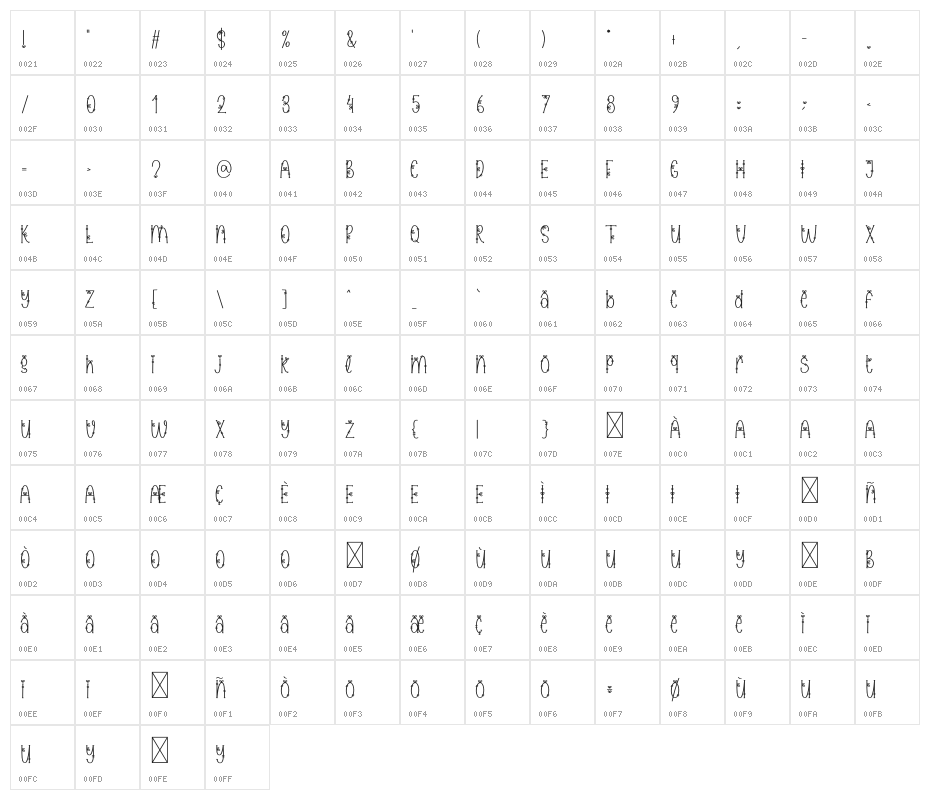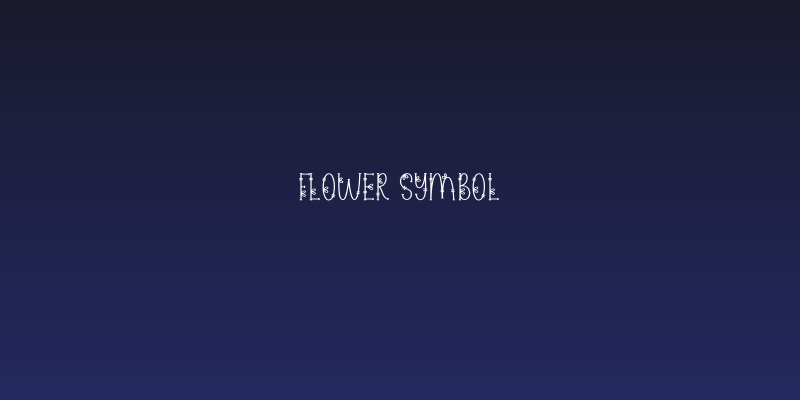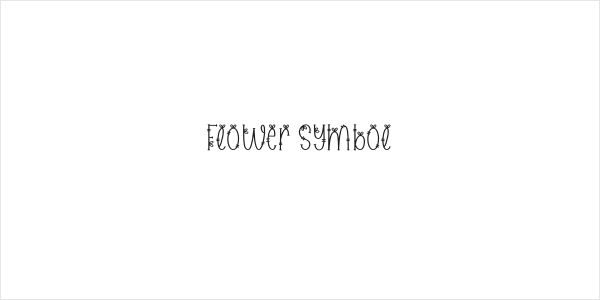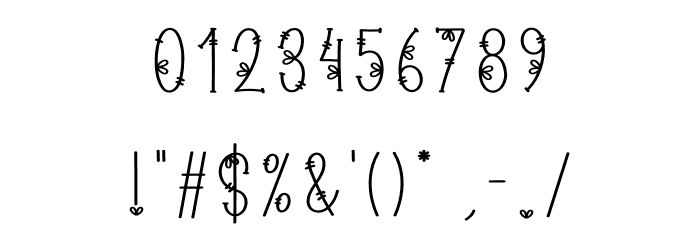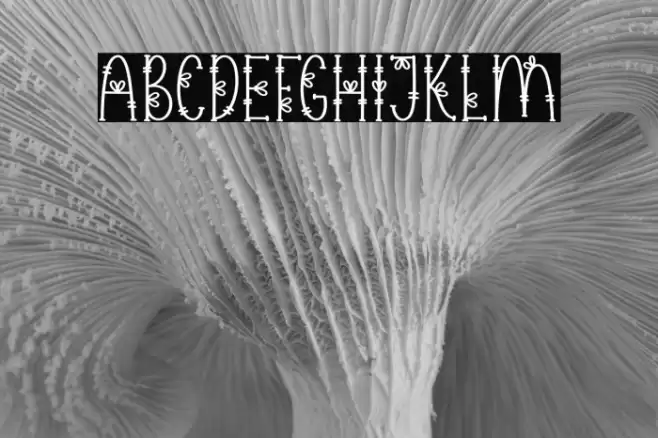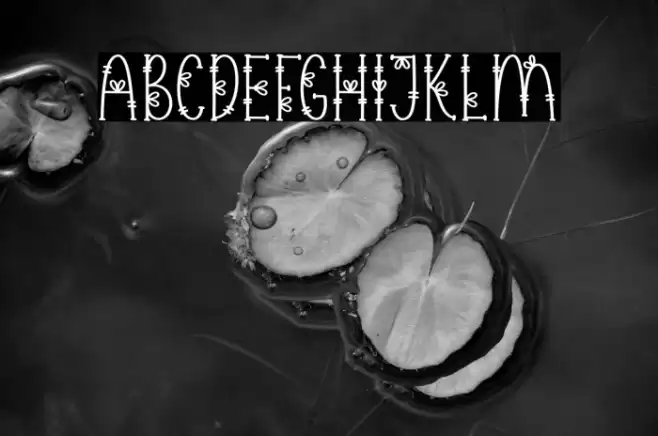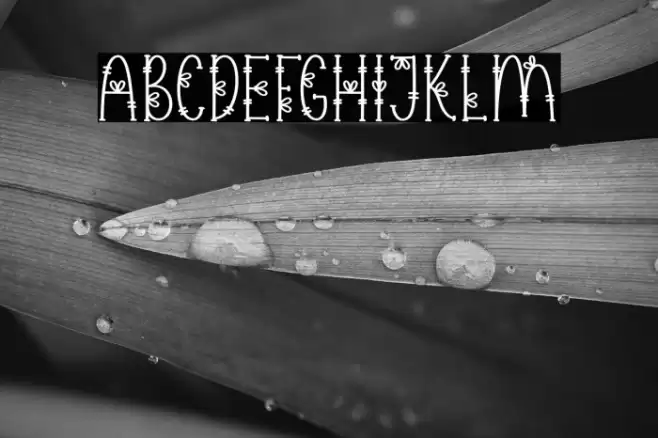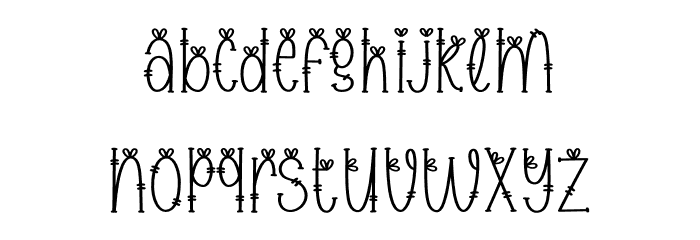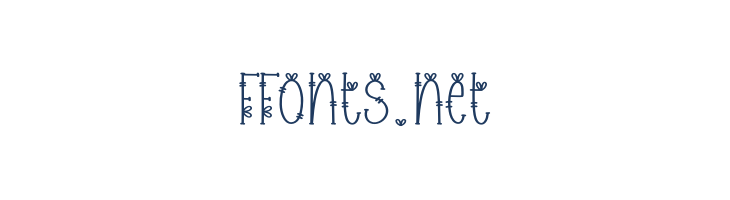
Flower Symbol Font
| Caz de utilizare | Headlines, Logos, Artistic designs |
| Proiecte propuse | Ideal for greeting cards, invitations, posters, and any design needing a whimsical, nature-inspired touch. |